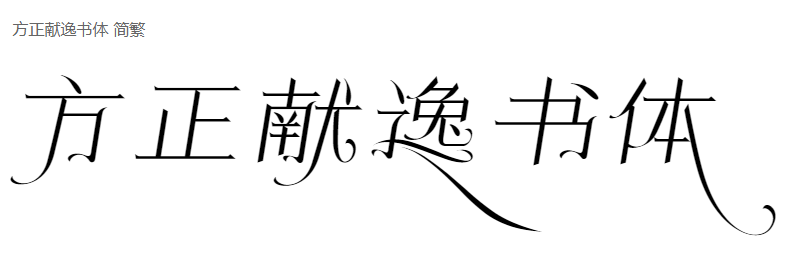
方正献逸书体
字体介绍:
方正献逸书体是以英文手书装饰体(花体)的风格结合中文宋体为基础,遵循手书汉字的运笔习惯,将部分适宜笔画夸张延伸的文字进行了艺术加工处理,以求突破传统方块汉字的设计手法,为中文汉字表达的多样化提供更多的选择。
参考英文四横线三段式书写规范,本字体采用五横线四段式,将文字的识别主体放在上方第一线和第二线之间,夸张延伸的笔画安排在下方间隔不等的三段范围内,形成三种不同长短规格的笔画延伸长度。外框规范采用规则多边形连续横排的形式,将文字笔画的识别主体(左、上、右)保持在斜方框内,每行字的上方保持一条水平直线,左右保持同等的字间距,维持阅读的整体感,而向下方和右下方的延伸笔画线条留有足够的伸展空间,可令人产生一种舒畅活泼的动态观感。
尽量简化传统的笔画形态,在保持可读性的前提下统一笔画的形态,让文字的视觉效果更具整体性。
本字体可应用在诗歌排版、抒情文案、旅游推介、MV歌词、交友平台等方面,为人们情感赋之文字的表达增加更多的选择。
方正献逸书体
设计师: 陆显献